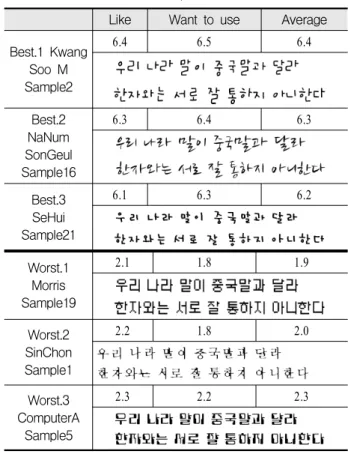
한글글꼴에 대한 한국인과 중국인의 감성분석
Sensitivity Analysis on Korean Fonts Between Korean and Chinese
The purpose of this research is to provide objective information about Korean and Chinese’s sensitivity and preference among various Korean fonts, and offer guidelines for using it. Firstly, to analyze Korean fonts in objective way, We compared about image of Korean fonts to Chinese who feel unfamiliar with Korean letter, and proved how different from Korean’s opinion. Secondly, one compared preference in particular fonts between Korean and Chinese. Through the factor analysis, the results are as follows. First, Korean and Chinese feel the same about the two groups of factors. There are differences in the rank, but the majority of fonts are included in the same group. It can be concluded that both Korean and Chinese has similar sensitivity about Korean fonts. Second, while Korean and Chinese decides preference on the familiarity, Chinese who are not familiar with Korean letters, have tendency to prefer calligraphic font which they have been using in the Chinese letter.
본 연구는 디자인 요소로 한글을 사용하려 할 때 다양한 한글글꼴에 대한 감성과 선호도에 대한 객관적 정 보 제공하여 한글글꼴 사용에 있어서의 방향 제시를 돕고자 하는 목표를 가지고 있다. 연구의 세부 목표는.
첫째, 한글글꼴의 조형 요소를 좀 더 객관적으로 분석하기 위해서 한글을 전혀 모르는 중국인을 대상으로 한 글글꼴에 대한 감성 차이가 한국인하고 어느 정도 차이가 있는지 분석하였다. 둘째, 글꼴에 대하여 한국인과 중국인들의 선호 비선호를 비교 분석 하였다.
첫 번째 목표를 밝히기 위해 요인 분석을 실시한 결과, 한국인과 중국인이 모두 2가지 대표요인으로 [친숙 성], [soft]가 추출되었으며 양국 모두 제 1요인과 제2요인의 소속요인 모두가 순위의 차이는 있었지만 대다수 가 공통적으로 가지고 있어 한국인과 중국인들이 한글글꼴에 대하여 서로 비슷한 감성을 가지고 있음을 알 수 있다.
두 번째 한글글꼴 선호도 분석을 실시한 결과, 한국인 및 중국인의 선호도를 결정하는 가장 큰 요인은 친 숙성이라고 볼 수 있고, 한글을 전혀 모르는 중국인들 또한 중국문화에 애용하여 왔던 붓글씨적인 서체를 선 호하는 경향이 있었다.
1. 서론
한글은 정보를 전달하는 매개체로서 우리의 일상생 활에 빈번하게 사용되고 있다. 이미 책과 신문 등의 매체에는 한글만을 사용한 지 오래되어, 이제는 많은 사람들이 한글과 한문이 같이 사용하는 문장을 낯설 게 생각할 정도가 되었다. 한글은 우리말이기 때문에 우리에게 가장 친숙하고, 빠르게 의미를 전달 할 수 있다는 장점이 있다. 또한 그 창제 원리가 과학적이고 디자인의 요소가 단순하면서도, 각 자음과 모음이 조 합된 글자가 매우 아름답다는 미적 장점도 가지고 있 다.
최근 들어 우리나라에서는 다양한 한글글꼴들이 개 발되고 있고, 웹 상에서 자신의 정체성을 글꼴을 통해 표현하는 등 한글글꼴의 이미지는 더욱 중요하게 부 각하고 있다.
현재 한류의 바람으로 중국뿐만 아니라 다른 아시 아 지역에서도 한글이 쓰여져 있는 옷을 입고 다닐 정도로 한글은 점점 국제화가 되어 가고 있는 시점이 다. 그러나 이러한 한글 전용의 현 상황과 한글 사용 의 장점들에도 불구하고, 우리는 한글을 디자인 요소 로 사용에 있어 적극적이지 못한 점이 있다. 이러한 현상에 대한 원인으로 첫째, 의미를 잘 전달하면서 미 적 아름다움을 가져야 하는 간판이나 기업의 로고, 제 품의 패키지나 상품명 등의 디자인에 한글보다 영어 를 사용하는 것이 좋다고 생각하고 있다는 점과 둘째, 디자인 요소로 한글을 사용하려 할 때 각 한글 디자 인에 대한 선호도와 감성 효과에 대한 객관적 정보의 부재를 들 수 있다. 따라서 이러한 디자인 현실을 극 복하고, 한글을 디자인 요소로 사용하여 우리 디자인 의 장점으로 삼을 수 있도록, 한글에 대한 감성 분석 연구가 시급하다고 할 수 있다.
이에 본 연구는 한글이 세계에 알려지면서 한국인 과 중국인을 대상으로 한글글꼴에 대한 감성분석을 실시하여 첫째, 한국인과 중국인들이 한글글꼴을 보 고 가지는 주요 감성은 무엇이며, 어떤 기준으로 평가 를 하는 지 분석한다. 둘째, 한국인과 중국인들은 어 떤 한글글꼴 디자인을 좋아, 싫어하는지 그 선호를 알 아보고, 선호, 비선호 하는 한글글꼴의 조형적 특징을 알아본다. 이러한 연구결과를 이용 하여, 한글글꼴을 디자인 할 때와 중국에서 한글글꼴을 디자인 요소로 활용하고자 할 때 방향이 되고자 한다.
2. 이론적 배경과 연구 목적
기존 연구를 분석해 보면, 연구가 초기 단계이고 그 수도 적은 점을 알 수 있다. 기존 연구의 대부분은 새 로운 한글글꼴의 디자인 제안에 관한 것이고(김명담 (1982), 백윤수(1988), 이기수(1993), 김성학(1995), 김 성희(1999), 황수홍(2000)), 그 밖에 한글 디자인의 응 용 분야에 관한 연구(성혜현(1987), 황화선(2000), 김 경실(2002)), 타이포그래피로서의 한글의 가치에 대한 연구(박미정(1999)), 한글 디자인의 흐름을 정리한 연 구(고선(2002)), 한글 디자인의 분류 체계에 대한 연구 (홍윤미(2002)), 한글의 가독성에 관한 연구(정우현, 한 재준, 정찬섭(1993)) 등이 있다. 한편 한글 디자인의 감성적 효과를 분석하여 한글 사용에 관한 지침을 주 고자 하는 연구도 진행되었다(최동찬(2000)). 그러나 이 연구에서는 연구자 임의로 한글의 종류를 나누고, 연구자가 각 분류에 대표된다고 생각되는 글자체를 임의로 하나씩 총 4개만 선택하여 감성 효과를 분석 하고 있다. 이는 새로운 한글 디자인을 할 때나, 디자 인된 한글을 사용할 때 제한된 정보를 제공하여, 사용 자가 한글 디자인을 평가에는 한계가 있었다. 장현정, 윤형건(2003) 연구에서는 첫째, 한국인들이 한글글꼴 을 평가할 때 어떤 감성 기준으로 평가를 하는 지 그 리고, 둘째, 사람들은 어떤 한글글꼴 디자인을 좋아하 는지 그 선호도를 알아보고, 선호하는 한글 디자인의 조형적 특징을 알아보았다, 그 결과 한국인들은 여러 매체를 통하여 인지된 익숙한 글씨체를 선호하는 경 향을 보였다. 이에 본 연구에서는 한글글꼴의 조형 요 소를 좀더 객관적으로 분석하기 위해서 한국인과 한 글을 모르는 중국인을 대상으로 이미지 분석과 선호 분석을 실시하였다.
3. 연구의 방법
본 연구는 한글을 디자인 요소로 사용하기 위해 한 글글꼴에 대한 감성 공학적 연구 방법을 적용 하였다.
순수하게 한글의 조형성을 분석하기 위해서 한글을 읽고 쓰지는 못하지만 조형적으로 한글 이라는 것은 아는 중국인과 한국에서 정상적 의무교육을 받은 한 국인을 대상으로 비교분석하였다. 그리고, 본 연구샘 플은 1470개 서체에서 굵기, 기울기, 중심선, 쉐리프 유무 등을 고려하여 32가지 샘플 선정한 장현정, 윤형
No. Font Example No. Font Example
1 SinChon
(신촌) 2 Kwang Soo M
(광수 M)
3
HaeBa RaGi (해바라기)
4
EunDi NaRu (은디나루) 5 ComputerA
(컴퓨터 A) 6 Script
(필기체)
7 PaDo
(파도체) 8 URin
(우린체)
9
HeadlineM (헤드라
인 M)
10
Gungseo B (궁서B)
11 Sol
(솔체) 12 AnSang Su
(안상수체)
13
MulBangWool B (물방울B)
14 KkuReoGi (꾸러기)
15 EonHae M
(언해 M) 16
NaNumSonGeul (나눔손 글씨펜) 17 JongIHak
(종이학) 18 GeulKkot
(글꽃체)
19 Morris
(모리스) 20
ByeolNan SoNyeon (별난소년)
21 SeHui
(세희체) 22 WooRi
(우리체)
23 YeopSeo
(엽서체) 24 PyeonJi
(편지체) Table 1. Sample of Korean fonts
건(2003) 연구의 샘플을 기본으로 현재 사용빈도가 적 은 20개를 제외하고 새롭게 사용빈도가 많은 글꼴을 선정하기 위하였다. 그러하기 위해, 윈도우 XP에서 사용하고 있는 한글글꼴 370개에서 기본적으로 굵기 는 중간 굵기로, 중심선에 있어 일정한 것과 변화하는 것이 있었는데 일정한 것으로, 기울기가 있고 없음에 있어 기울기가 없는 것들을 선정 대상으로 정 한 후 사용빈도가 비교적 많다고 생각한 글꼴 12개를 선정 추가하여, 장현정, 윤형건(2003)의 연구의 샘플 12와 합하여 총 24종의 샘플을 선정하였다. 그리고, 다차원 척도법(Multi Dimensional Scaling)과 KJ법으로 추출된 18개의 형용사를 통해 감성이미지를 조사하였다. 분 석의 방법으로는 통계분석 방법 중의 하나인 요인 분
석을 사용하여, 감성 요인을 추출하였다. 마지막으로 선호된 한글글꼴의 이미지와 디자인 요소를 분석함으 로써 한글글꼴을 사용하는데 방향을 제시하였다.
3.1 한글 디자인 샘플 선정
[표 1]은 24종의 대표 샘플을 선정 후 아래의 조건 으로 샘플을 제작 하였다.
1) 가로 : 525픽셀(약 18.52cm) 2) 세로 : 100픽셀
3) 테두리 : 없음
4) 해상도 : black or white
5) 글자 크기 : 36point 6) 파일 형식 : jpg 7) 파일 크기 : 30kb 이내
8) 내용 : 아래의 내용 및 띄어 쓰기, 정렬 유지
“우리 나라 말이 중국말과 달라 한자와는 서로 잘 통하지 아니한다”